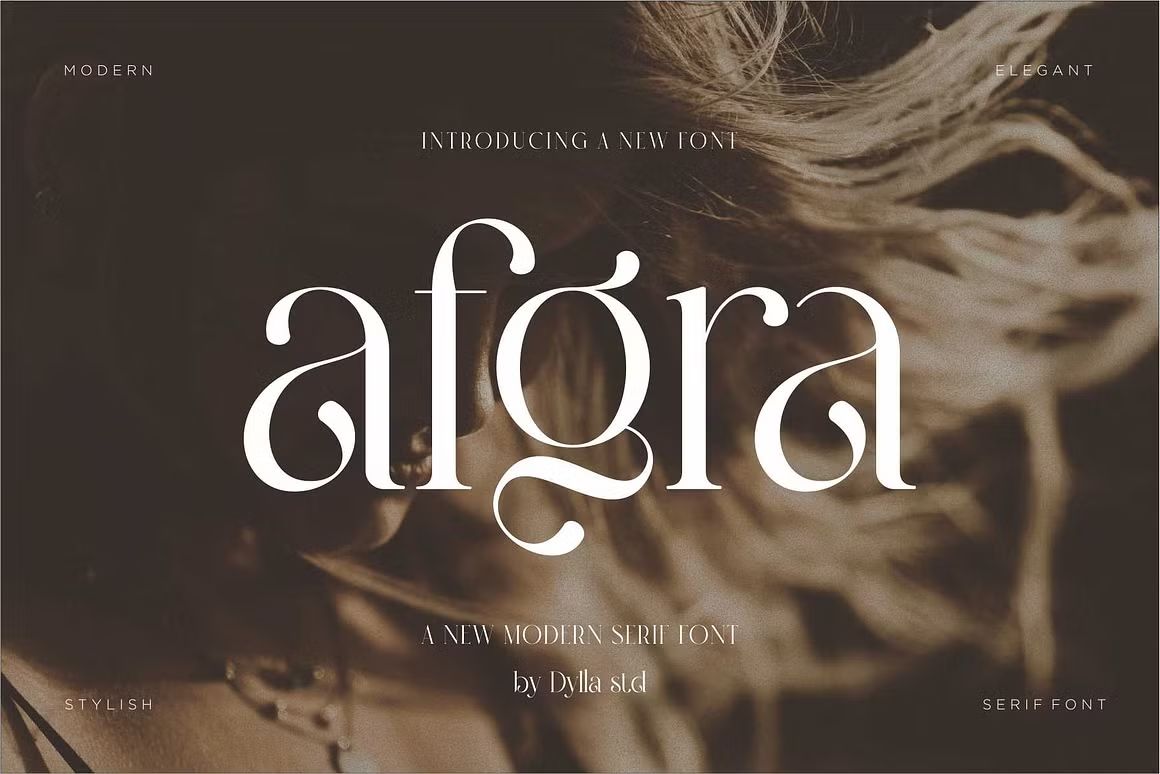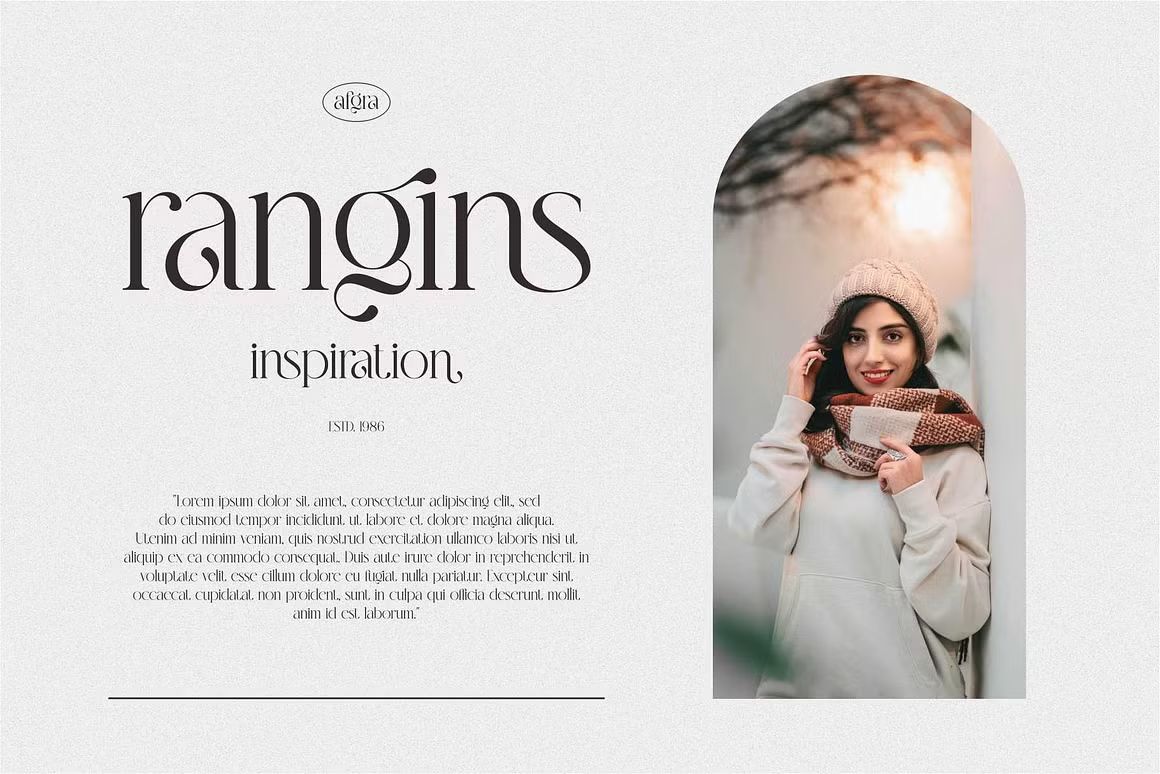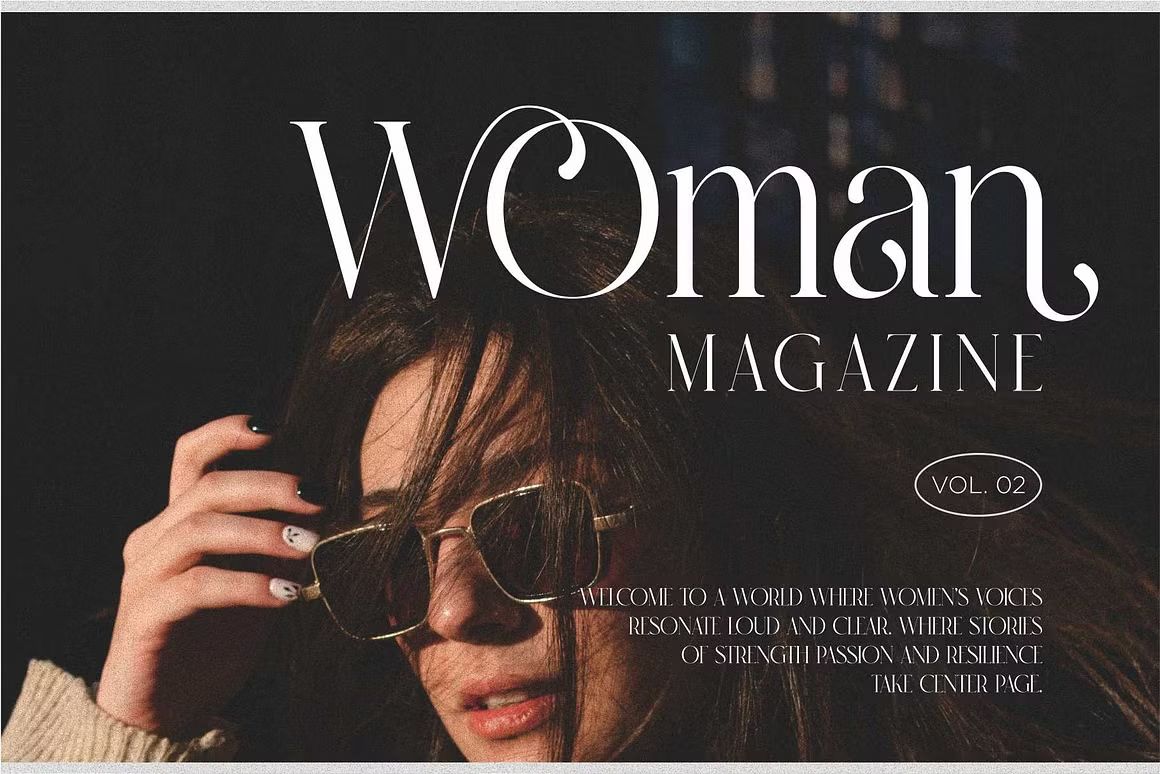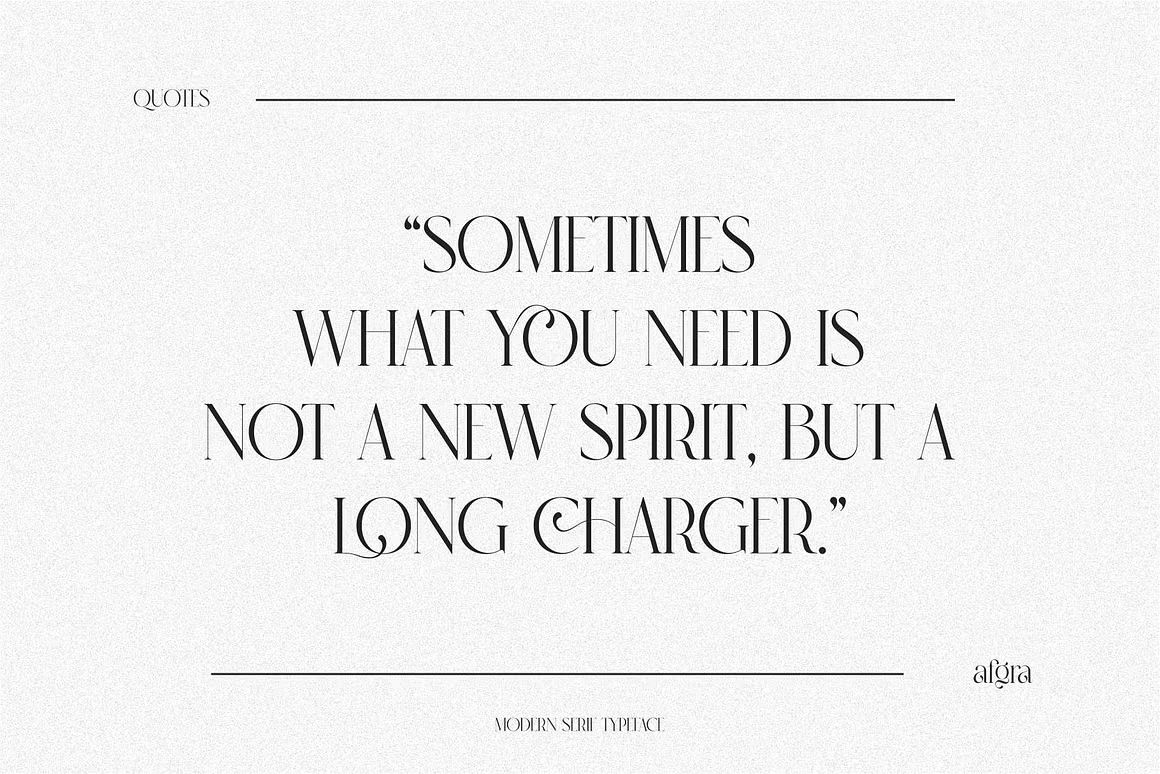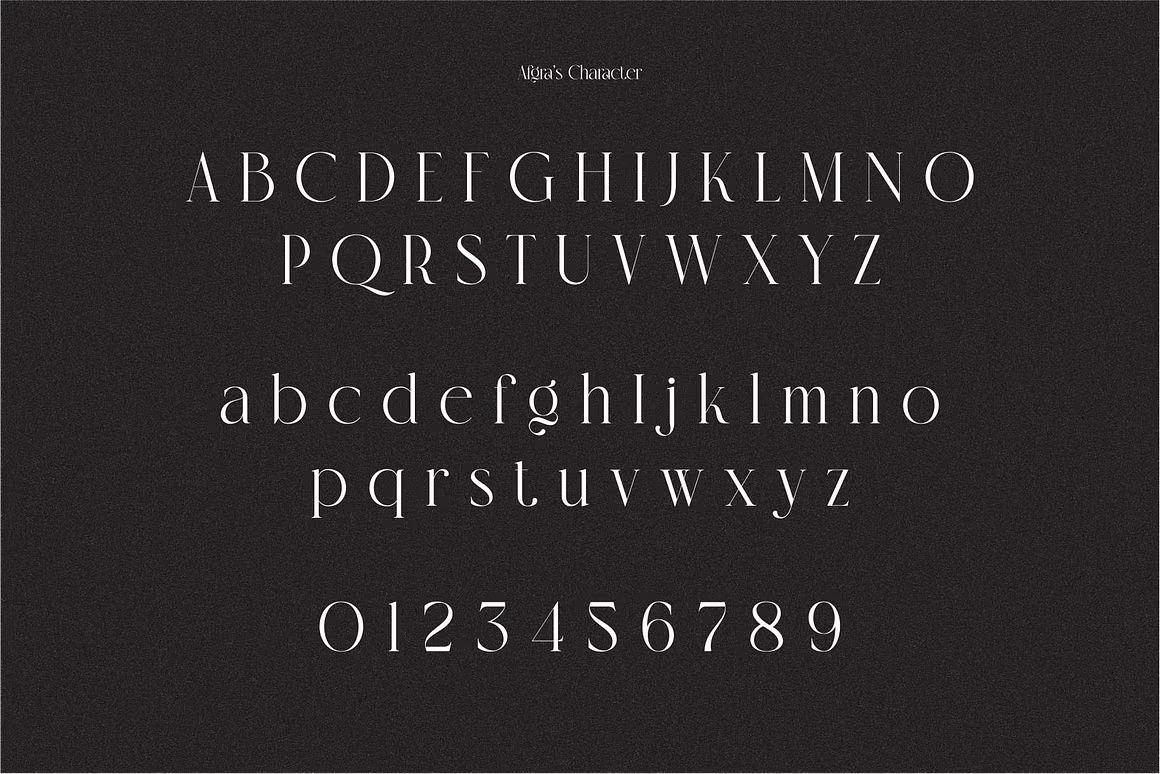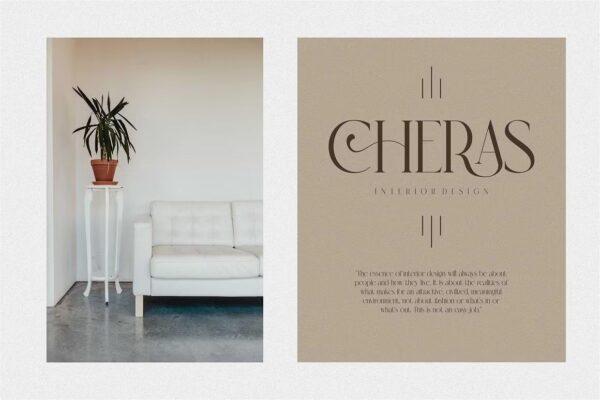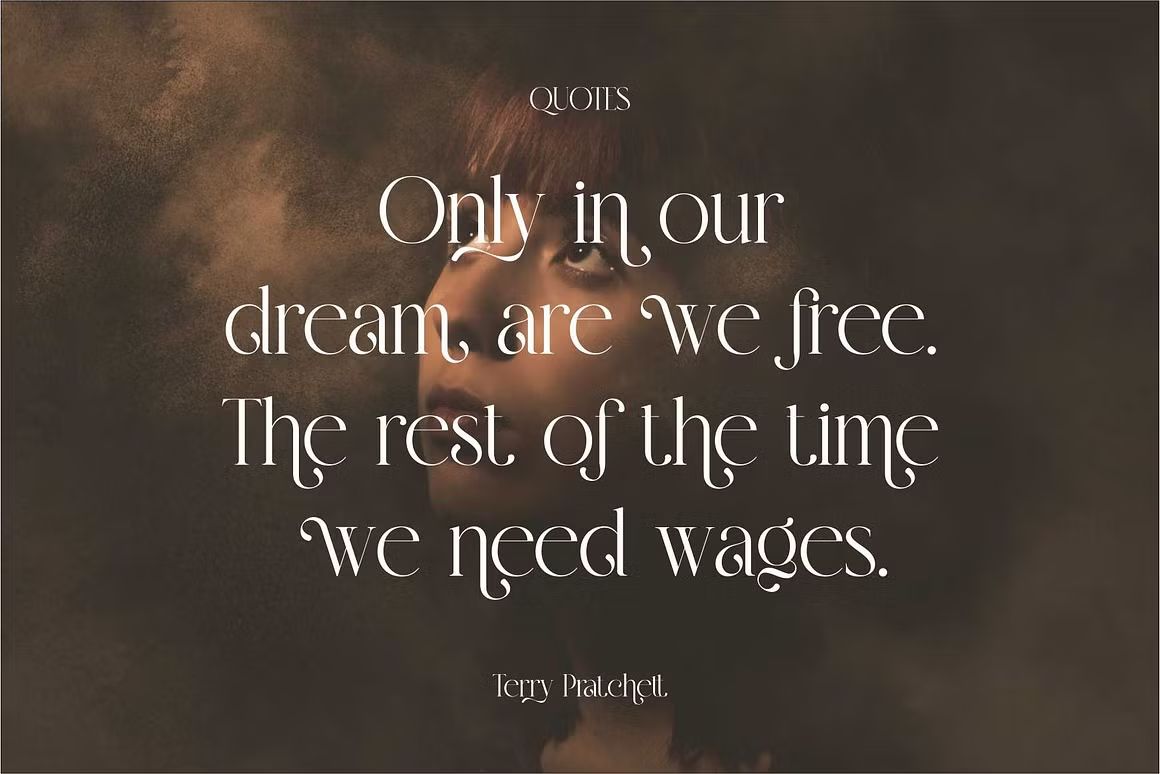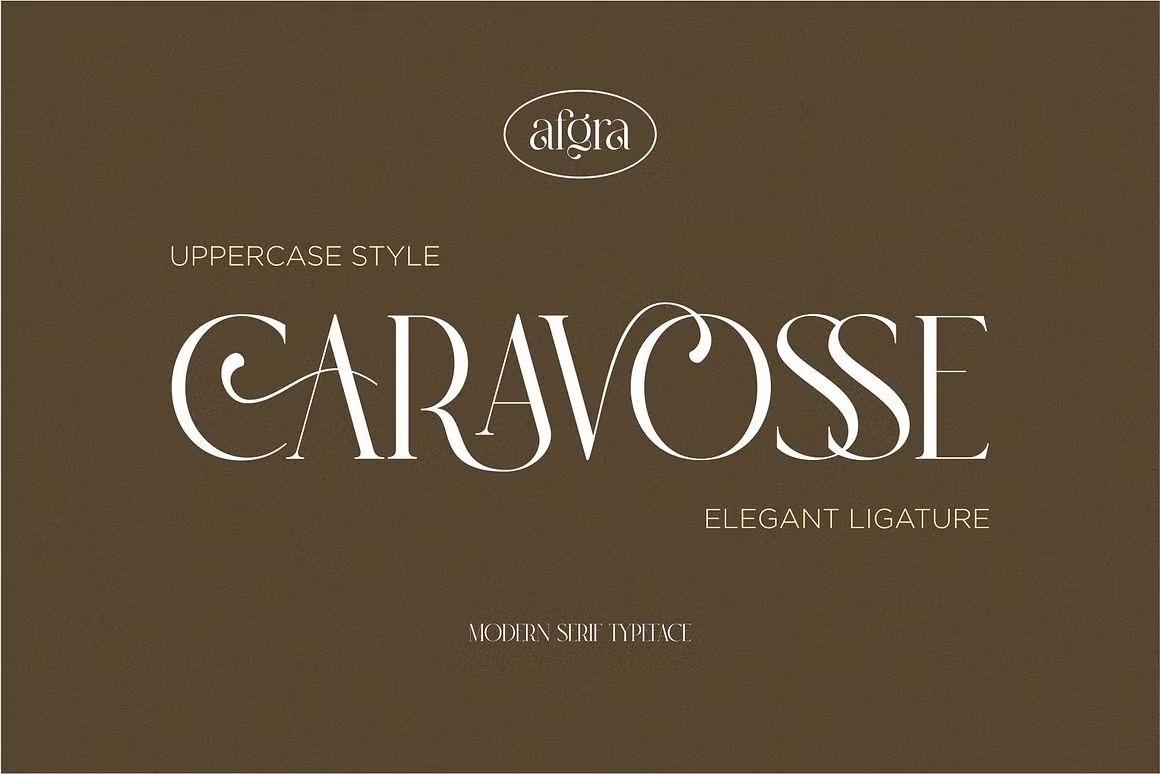
Afgra – Sans Serif Font
Afgra adalah font sans serif modern dan minimalis, ideal untuk branding dan desain profesional. Format OTF/TTF/WOFF, siap digunakan.
Afgra adalah font sans serif modern dengan gaya tegas dan minimalis. Menggabungkan bentuk huruf geometris dan struktur yang bersih, font ini cocok untuk berbagai kebutuhan desain seperti branding, editorial, kemasan, web design, dan presentasi bisnis. Afgra memberikan tampilan yang profesional, kontemporer, dan mudah dibaca di berbagai ukuran.
• Sans serif modern dengan struktur bersih dan tegas
• Cocok untuk branding, editorial, dan desain digital
• Termasuk huruf kapital, kecil, angka, dan simbol